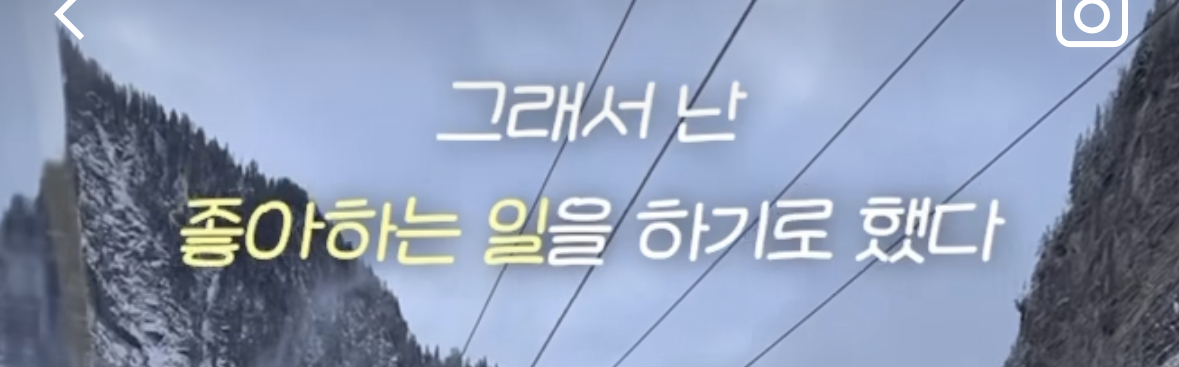
이 폰트 뭐에요? gyu*** 2023.04.18 손글씨 폰트 궁금합니다 댓글 0 등록 오타대마왕 https://www.sandollcloud.com/font/17229.html 이서윤체 입니다. 2023-04-18 답글 달기 댓글 더보기 쉽고 빠르게 가장 비슷한 폰트를 알고 싶다면? 이미지로 검색하기
https://www.sandollcloud.com/font/17229.html 이서윤체 입니다.